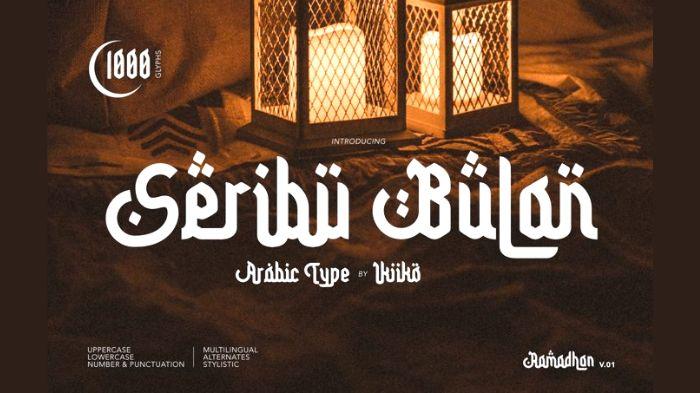
Kumpulan 20 Link Font Ramadhan, Cocok untuk Tulisan di Konten Instastory, Reels, dan TikTok
Ini kumpulan 20 link font Ramadhan yang cocok untuk tulisan di konten Instastory. reels, ataupun TikTok.
TRIBUNKALTIM.CO - Ini kumpulan 20 link font Ramadhan yang cocok untuk tulisan di konten Instastory. reels, ataupun TikTok.
Sebentar lagi, Ramadhan 2024 akan segera tiba, yaitu tanggal 12 Maret 2024.
Membuat konten bisa jadi salah satu cara merayakan semarak dan semangat Ramadhan.
Dalam membuat konten, maka penting juga untuk memilih jenis font yang akan digunakan.
Font bernuansa Ramadhan atau tulisan Arab, tentunya akan lebih cocok.